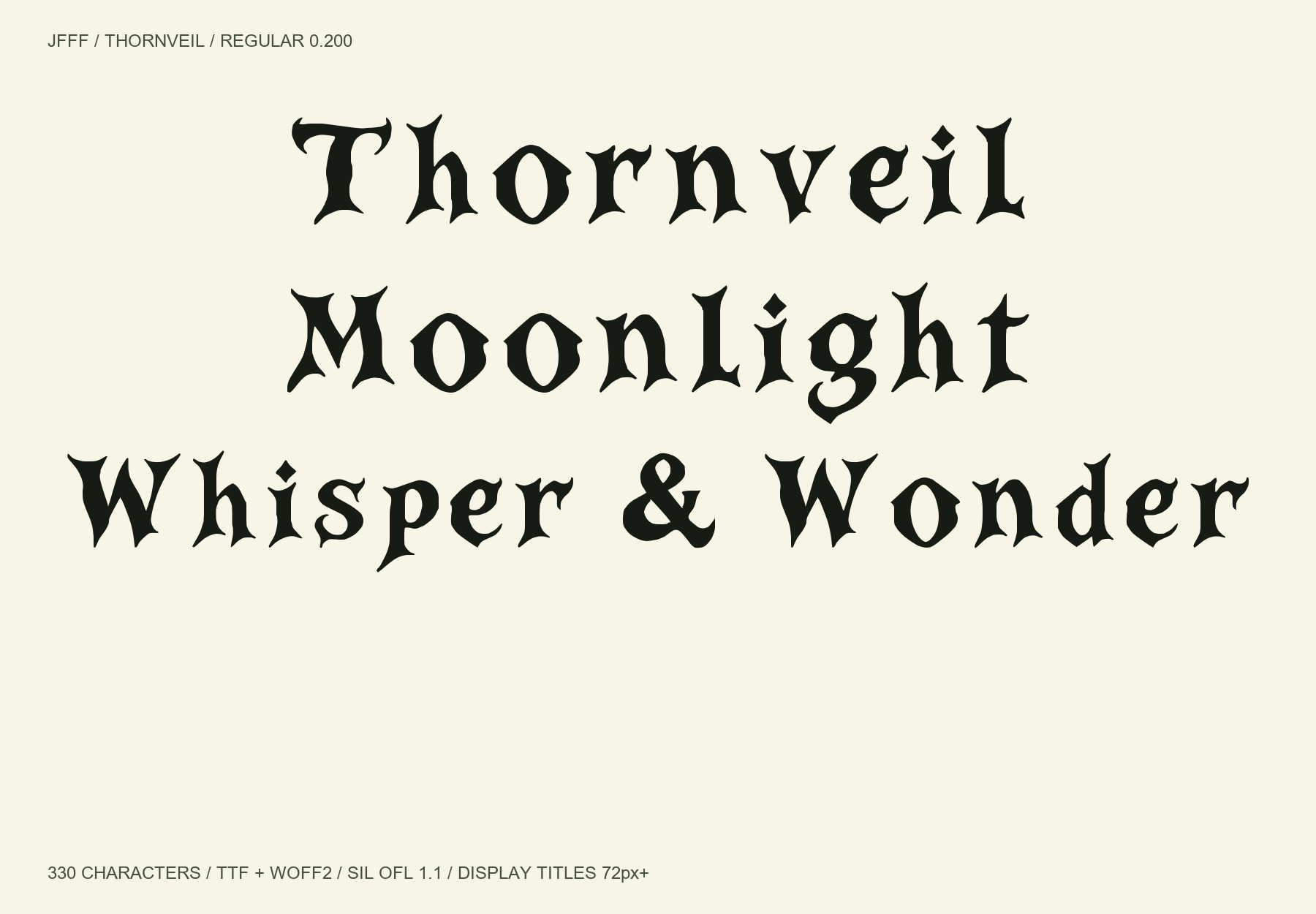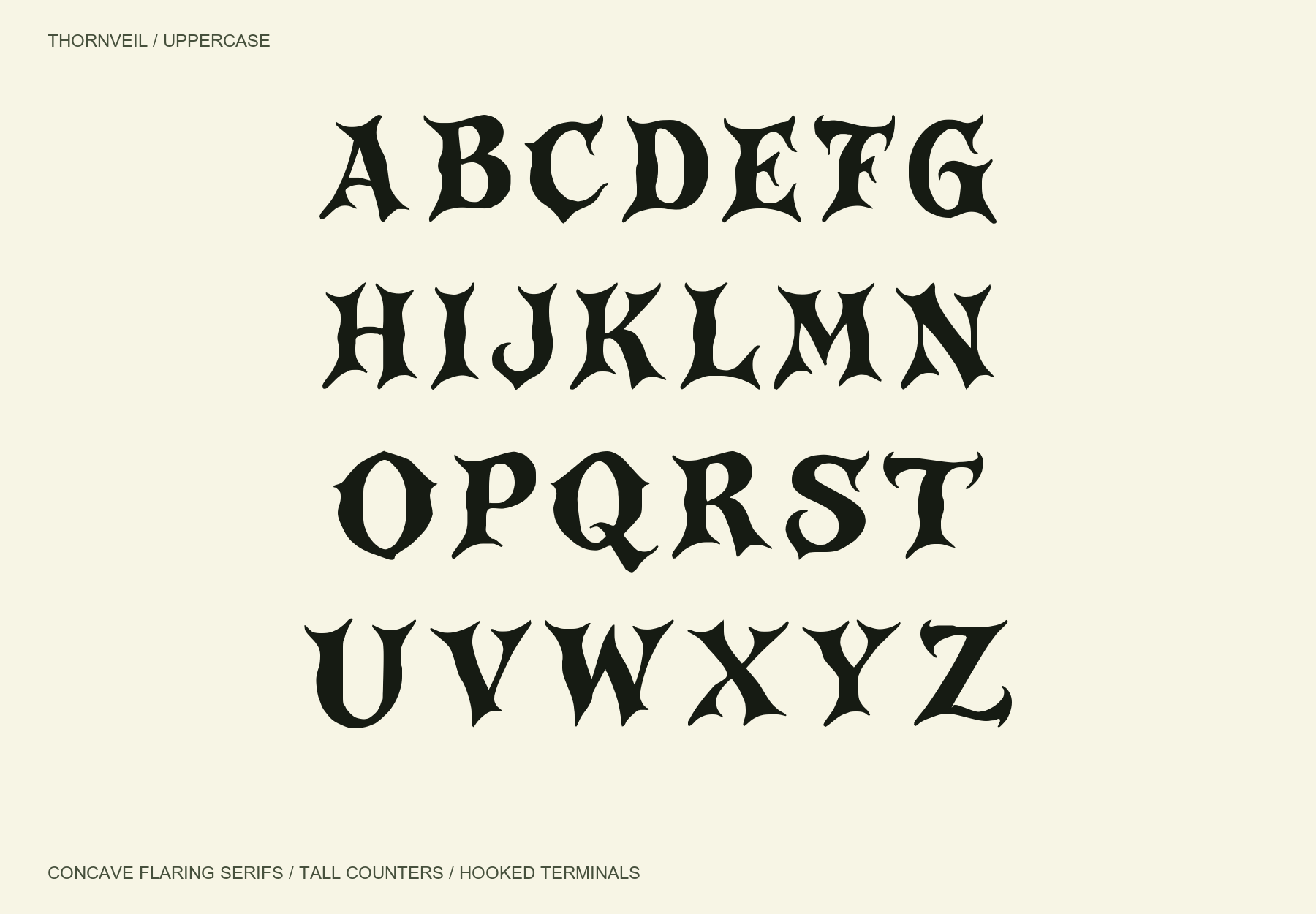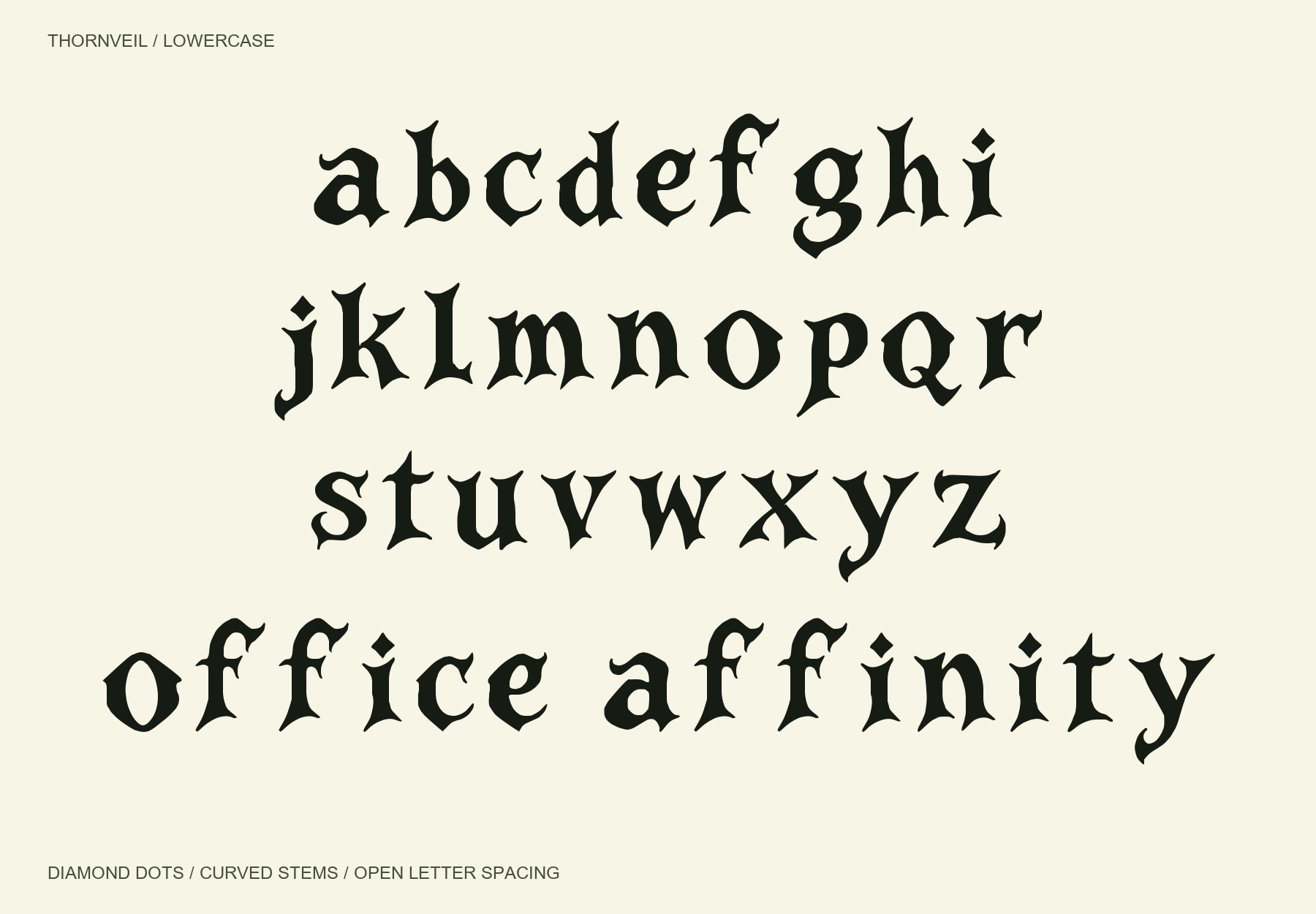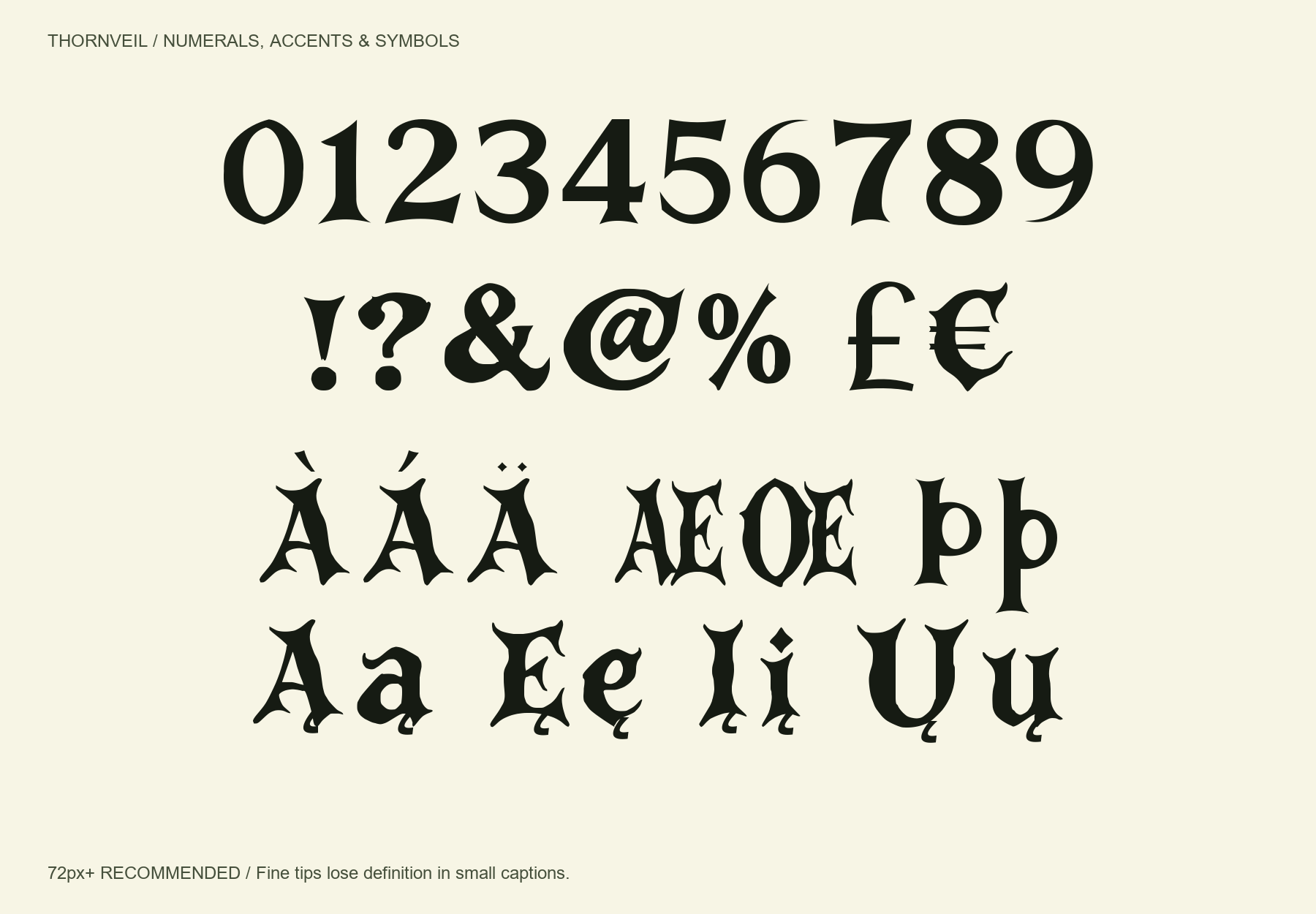
Free high-contrast serif font
Thornveil은 안쪽으로 휘어진 기둥과 뿔처럼 뻗는 세리프, 좁고 긴 속공간을 결합한 장식용 디스플레이 서체입니다. 갈고리형 끝부분과 마름모 점, 날카로운 곡선의 대비가 판타지 제목과 포스터에 어울립니다. 제공된 레퍼런스의 글자 형태를 재구성하고 숫자와 확장 라틴 문자를 추가했습니다. Regular 0.200 · 라틴 330자(표시 문자 328자, 공백·NBSP 2자). 영문 대소문자, 숫자, 확장 라틴 악센트와 기호를 지원하며 한글은 포함하지 않습니다. TTF와 WOFF2를 하나의 ZIP으로 제공하고 SIL Open Font License 1.1로 무료 배포합니다. 72px 이상 제목·포스터에 권장합니다. 작은 본문과 캡션에서는 가는 끝부분과 속공간이 약해질 수 있습니다. 17장 확대 표본으로 330자를 검토하고 i·j 악센트, £·Þ·þ 접합부, ¶의 작은 틈과 아래 악센트 연결을 수정했습니다. 커닝 285쌍을 반영했으며 108,900개 문자 조합의 윤곽 경계 검사에서 겹침이 발견되지 않았습니다. Windows GDI 출력과 Edge·Chrome 웹폰트 로딩 및 커닝을 확인했습니다. macOS와 Adobe 앱은 미검수입니다.